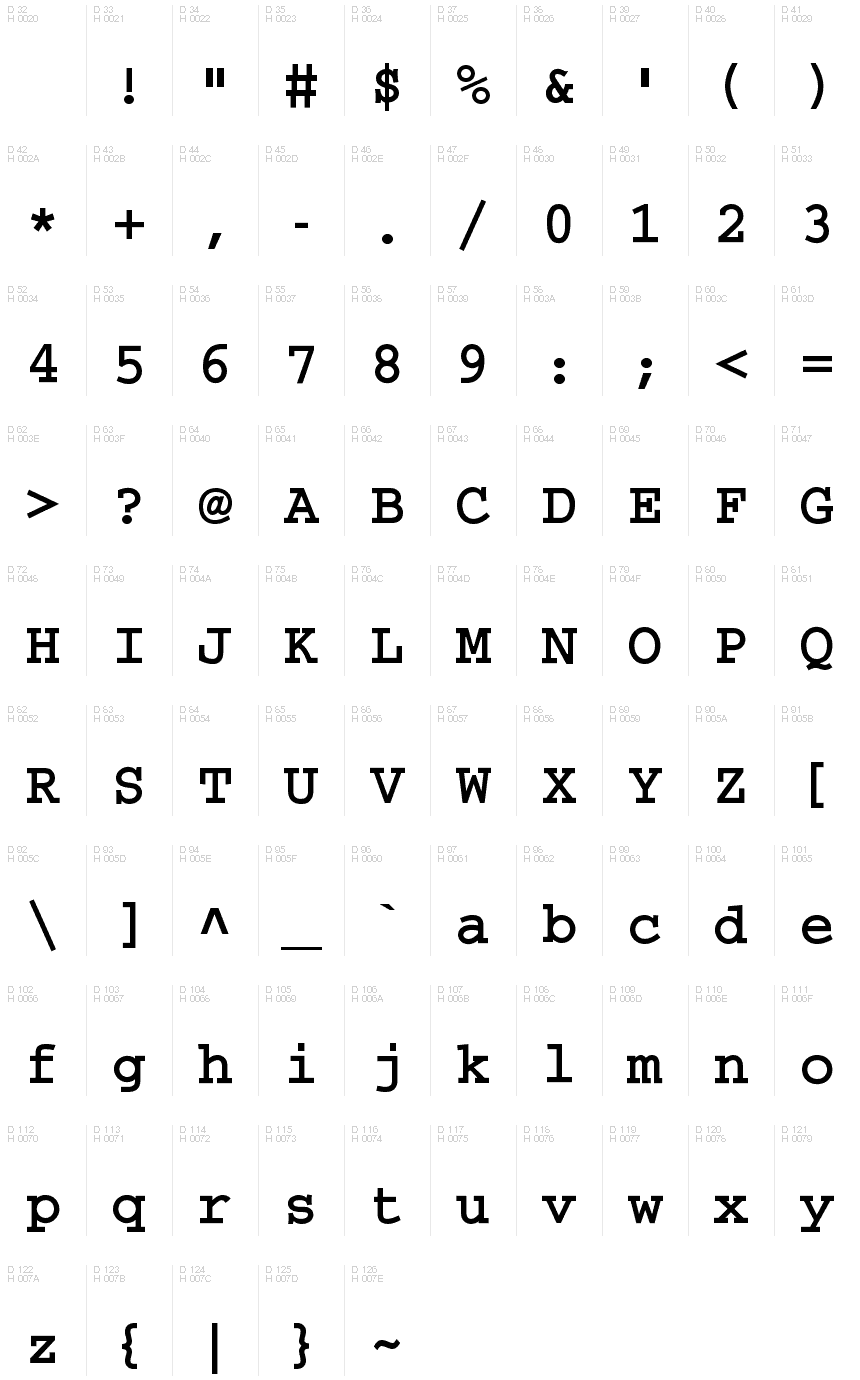
Ethiopic WashRa Bold od Senamirmir Project je bezplatné patkové písmo s umírněným, klasickým tiskovým charakterem. Písmena kombinují masivní, téměř blokové horní části se zaoblenými tvary a kompaktními spoji, což písmu dodává robustní rytmus. Ten působí spíše jako titulky starých novin nebo učebnic než jako uhlazený moderní branding.
Skvěle se hodí pro redakční nadpisy, kulturní plakáty, obálky knih, grafiku s nádechem archiválií a titulní karty, kde tato pevná, lehce účelová textura pomáhá udávat tón. Jako bezplatné písmo funguje dobře i pro krátké citáty a úvody sekcí, protože široké patky a jednoduché křivky působí uzemněně, nikoliv dekorativně.
Ethiopic WashRa Bold